Liệu rằng font chữ có thể làm nên độ tin cậy của thương hiệu?
Hãng Monotype đã giới thiệu thương hiệu của mình với Heart Collection, một bảng chữ có chọn lọc.
Việc sử dụng những mặt chữ này trong thiết kế bộ nhận diện thương hiệu chuyên nghiệp của hãng, theo một cách nào đó, đã mang lại cảm giác đáng tin cậy hơn với hình ảnh của hãng này.
Bộ sưu tập chữ này được tạo ra nhờ sự hợp tác hiện tại giữa Monotype và Lippincott, một hãng chuyên về thương hiệu toàn cầu. Bộ đôi này đã thiết kế bộ nhận diện thương hiệu mới và kiểu chữ cho hãng Southwest Airlines.
Monotype cũng đã sản xuất một phiên bản in ấn của bộ sưu tập chữ này.
Trong bộ hình ảnh được làm lại củaThe Southwest Airlines, chúng ta thấy tính kết nối của nó đã có sự tiến bộ
Khách hàng đang thay đổi
Rodney Abbot, đối tác cao cấp tại Lippincott nói rằng: " Trong những năm trở lại đây, khác hàng nhìn chung đã không còn tin tưởng vào những hình thức tuyên bố, tiếp thị màu mè và lớn tiếng của các công ty. Sự thay đổi này bắt buộc các doanh nghiệp phải biết lắng nghe ý kiến người tiêu dùng hơn, trở nên thực tế và cởi mở hơn, và truyền tải thông điệp theo một cách trung thực và đơn giản hơn.
Dự án thiết kế lại hình ảnh của hãng hàng không Southwest Airlines đã kéo theo nhu cầu tạo ra một kiểu chữ mới – Southwest Sans.
Nhìn sâu hơn vào cảm xúc
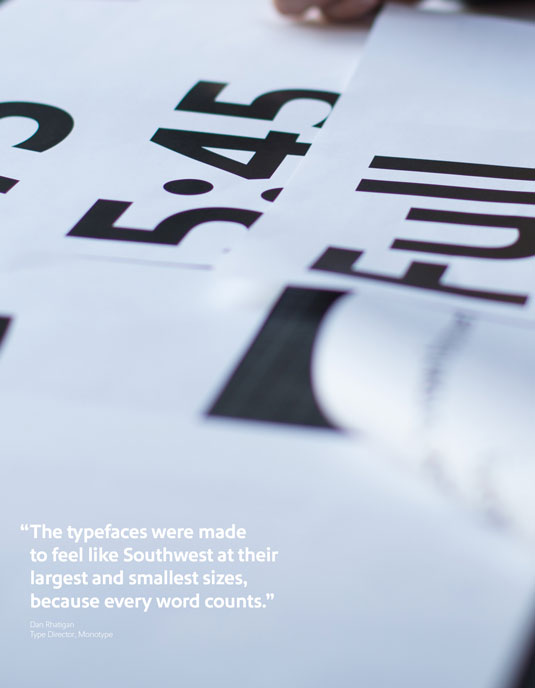
Southwest Sans là bộ chữ mang lại sự rõ ràng, thực tế và tạo cảm giác đáng tin cậy
Theo lời Giám đốc Monotype Dan Rhatigan, khi tham gia một dịch vụ, một mặt chữ có khả năng thể hiện rất nhiều trạng thái và cung bậc cảm xúc mà không làm mất cấu trúc ban đầu của chữ đó. The Southwest Sans typeface được thiết kế để mang lại cảm giác rõ ràng và chắc chắn dù cho nó xuất hiện trong thiết kế bộ nhận diện thương hiệu sáng tạo theo cách nào và bất kỳ kích thước nào.
Bộ sưu tập đáng tin
Logo cũng được thiết kế lại theo yêu cầu của dự án
Lấy cảm hứng từ sự thành công của Southwest Sans, hãng Abbot đã khám phá ra tầm quan trọng của typography trong việc khiến cho thương hiệu của mình có được ấn tượng về sự tin cậy và nhân văn. Công việc này trở thành dự ánThe Brands với Heart Collection.
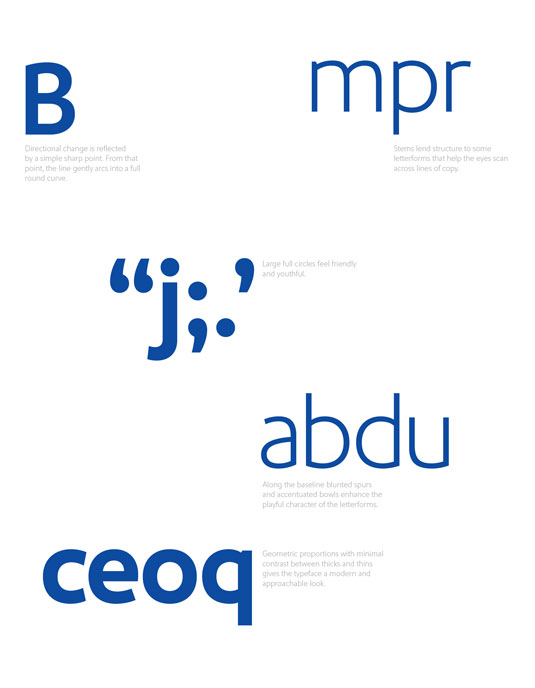
Các kiểu chữ có chất lượng khác nhau và một số chữ không rõ ràng, tác động đến cảm xúc và phản ứng của khách hàng
Abbot cho rằng truyền bá hình ảnh của thương hiệu mình và giao tiếp mới công chúng là một thách thức đòi hỏi chúng ta không được dối trá và bịa đặt. Các thương hiệu có được bộ sưu tập Heart collection sẽ tiến xa trong cuộc hành trình chinh phục công chúng.